今回は、力強さやスピード感を伝える「スポーツ」にぴったりな日本語フリーフォントをご紹介します。
スポーツの現場では、エネルギッシュで視認性の高い文字が求められます。スピード感あふれる斜体フォント、力強く太めのゴシック体、スタイリッシュで無駄のないサンセリフなど、競技の熱や選手の動きをダイレクトに表現できる書体が相性抜群です。
今回は、スポーツイベントのタイトルロゴやユニフォームの文字、YouTubeの試合実況サムネ、応援グッズのデザインなどにも使える、日本語フリーフォントをピックアップしました。パワフル・勢い・スピード感な印象を与えたいデザインに、ぜひ取り入れてみてください。
スピード感&力強さ!スポーツ系日本語フリーフォントまとめ
以下サンプル画像のように、スポーツにぴったりな勢い・スピード感・力強さが伝わるフォントをピックアップしました。以下以外にもたくさん紹介しているので、ぜひ参考にしてみてください。
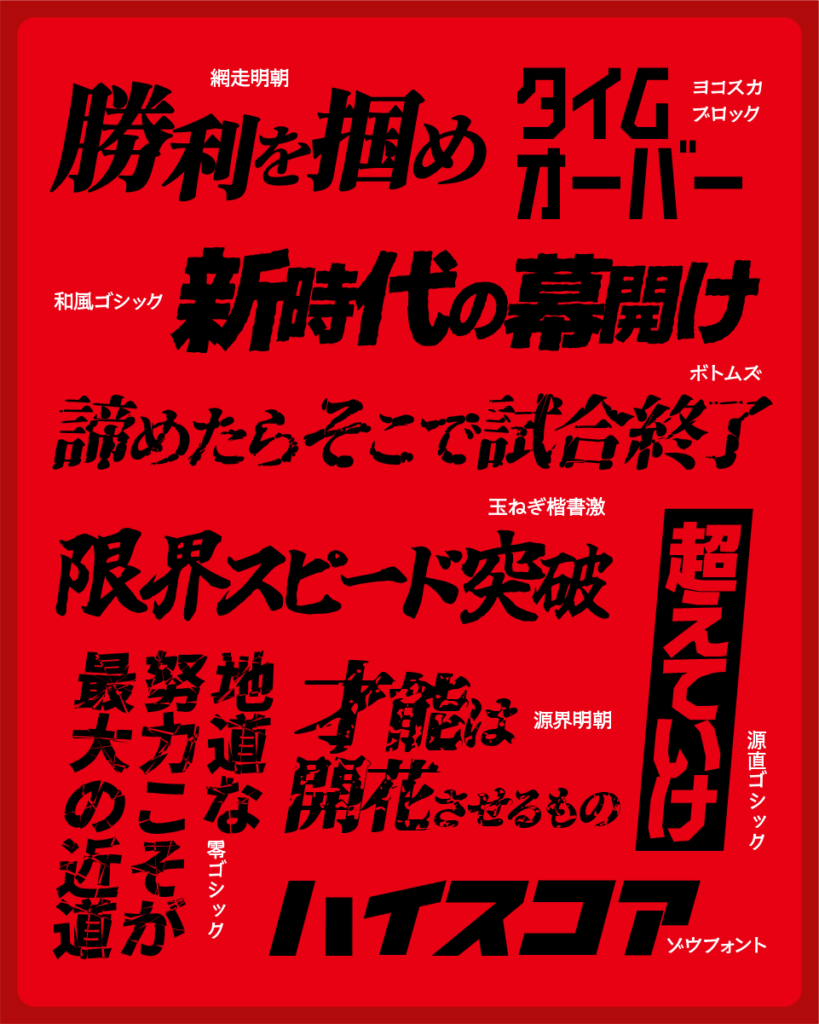
ゾウフォント
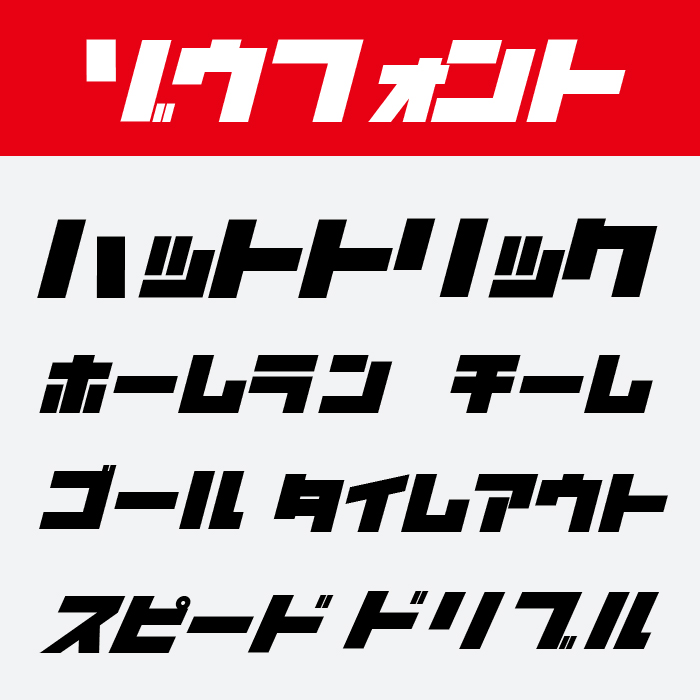
ゾウフォントは、角度のついた極太の骨格が力強さを際立たせ、疾走感と勢いを感じさせるフォントです。スピード感のある斜体のデザインが特徴で、サッカーや陸上競技などの動的な場面にもぴったりです。
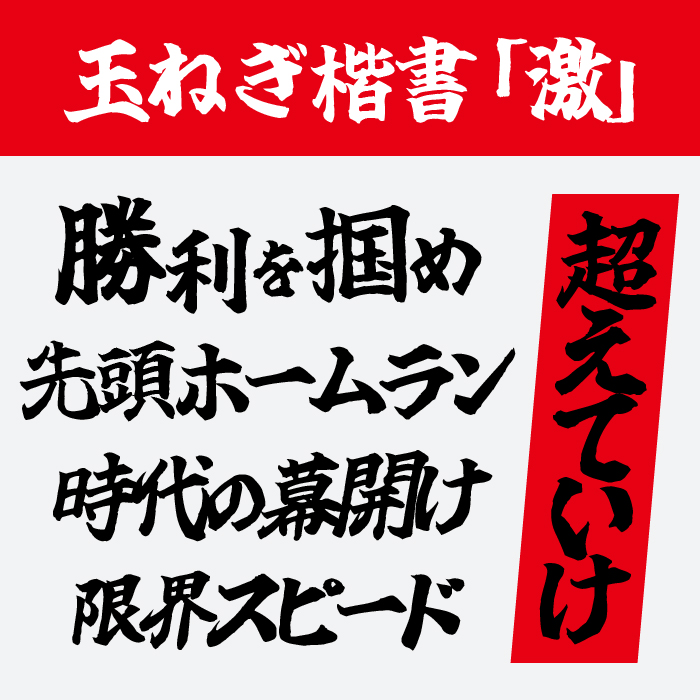
玉ねぎ楷書「激」フォントは、筆圧の強弱と荒々しい筆遣いが情熱を感じさせる熱血系フォントです。勝利や闘志を表現したいスポーツ系タイトルや応援のビジュアルにぴったりです。
キカカナ21
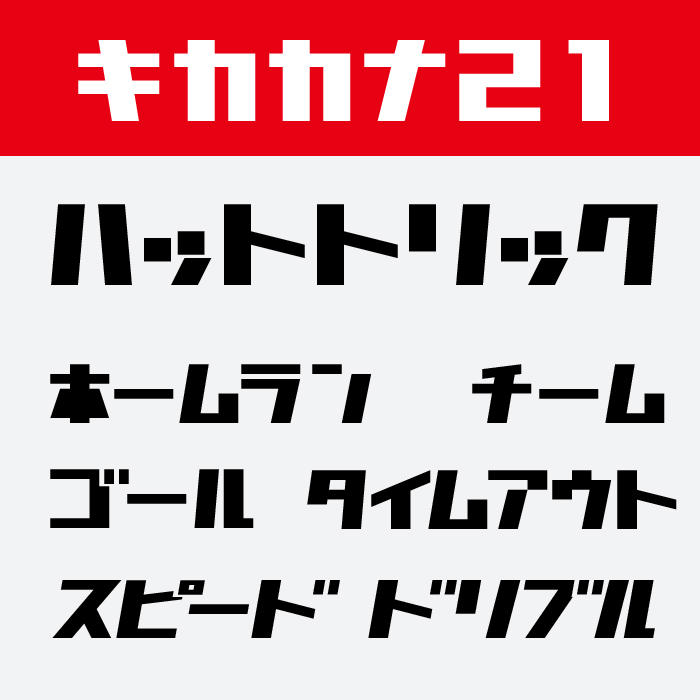
キカカナ21フォントは、直線的でエッジの効いたカナ文字が特徴のスポーティなフォントです。スコアボードやユニフォームのナンバーデザインなど、機能的でパワフルな場面にぴったりです。
ヨコスカブロック
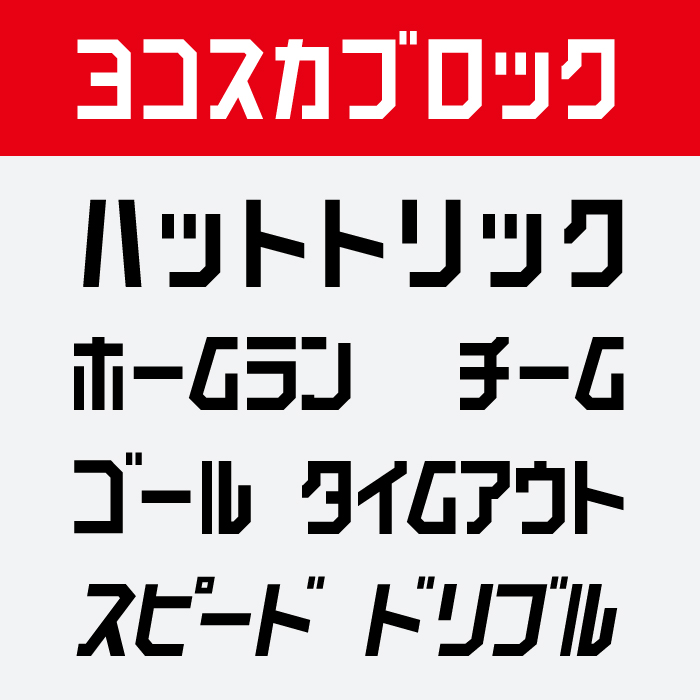
ヨコスカブロックフォントは、レトロフューチャー感のある無骨な形状が魅力で、野球やボクシングなど昭和テイストのスポーツ演出にぴったりです。力強さと懐かしさがあるような個性派です。
カクダロン
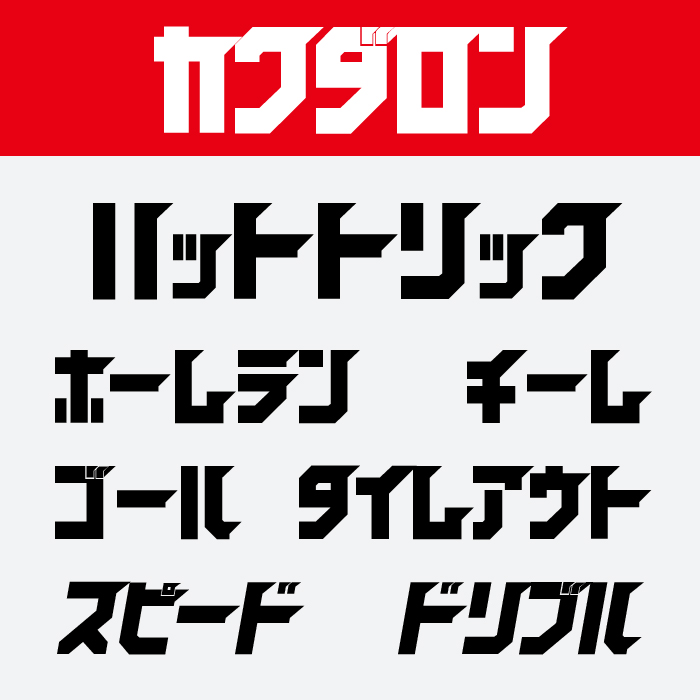
カクダロンフォントは、直線と斜線が交差するインパクト大のフォントです。とくに見出しで使えば競技の熱量や迫力を際立たせ、格闘技やストリートスポーツ系のタイトルにぴったりです。
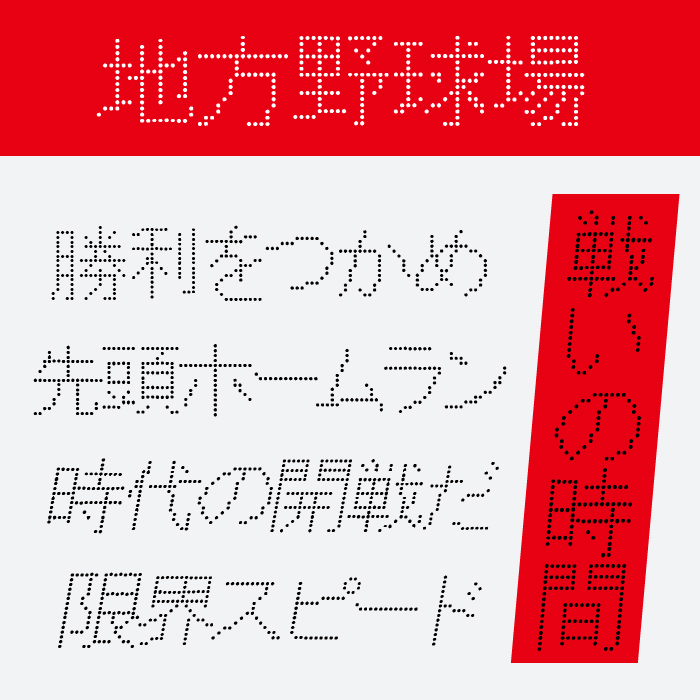
地方野球場フォントは、ドットで構成された文字が得点表示板のような味わいを持つフォントです。昭和の野球場やアマチュアスポーツの雰囲気を演出したいときにぴったりです。
零ゴシック
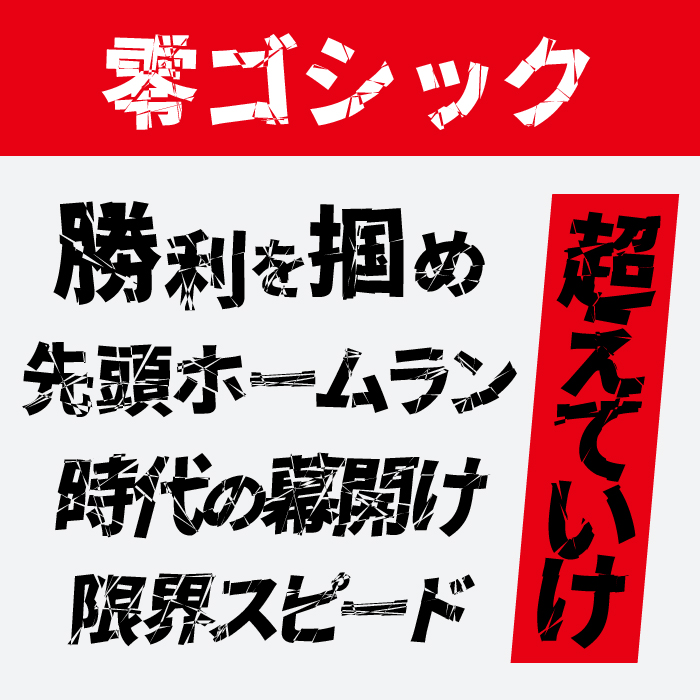
零ゴシックフォントは、破砕表現が施されたグランジ系ゴシックで、荒々しくもスピード感のある印象を与えます。限界突破、勝利、闘争心をテーマにした表現にぴったりです。
源界明朝
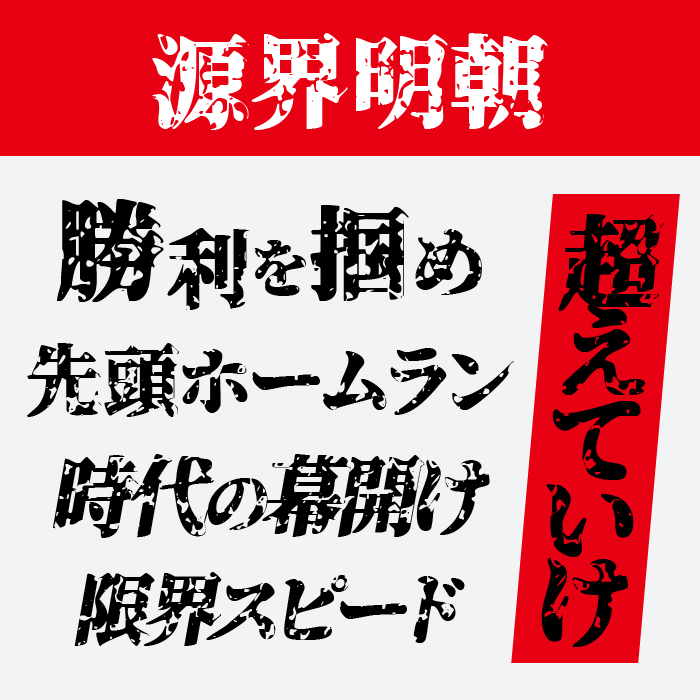
源界明朝フォントは、グランジ風に擦れやかすれ加工が加わった重厚感のあるフォントです。歴史的・伝統的な格闘技や武道の場面を、迫力と威厳を持って演出するのにぴったりです。
ボトムズG
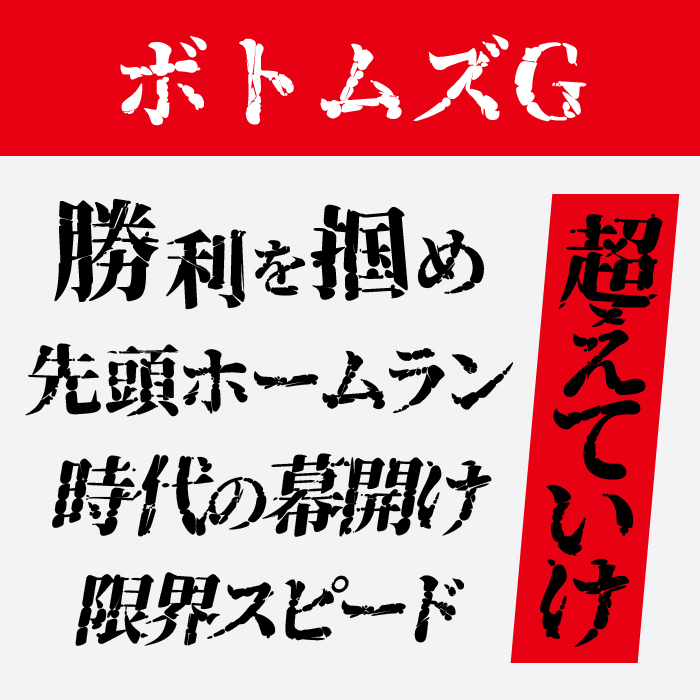
ボトムズGフォントは、輪郭に粉砕していているような質感の重厚さとグランジ感が融合した異色の明朝体です。泥臭さやタフな精神を表現したいスポーツ系タイトルにぴったりな、個性派フォントです。
網走明朝
網走明朝フォントは、クラシックな明朝体に力強さを加えたようなデザインで、重みと誠実さを併せ持ちます。相撲や武道など、伝統と品格を大切にするスポーツにぴったりです。
源直ゴシック
源直ゴシックフォントは、角張った力強いラインと直線的な骨格が特徴のフォントです。競技の瞬間的な緊張感や熱量をストレートに伝えたい場面にぴったりなフォントです。
和風ゴシック
和風ゴシックフォントは、文字の輪郭に少し粗さを取り入れたゴシック体で、力強さの中に土臭い野性味を感じさせるフォントです。アスポーツの中でも特に、根性・泥臭さ・勝負強さといった情熱を表現したいビジュアルにぴったりなフォントです。
Noto Sans
Noto Sansフォントは、均整の取れた現代的なサンセリフ体で、すっきりと読みやすいのが魅力のフォントです。明快さと清潔感を両立して、スポーツの公式ポスターやユニフォーム番号など、視認性が求められるシーンでも使いやすく、整ったデザインでスタイリッシュに演出できるフォントです。